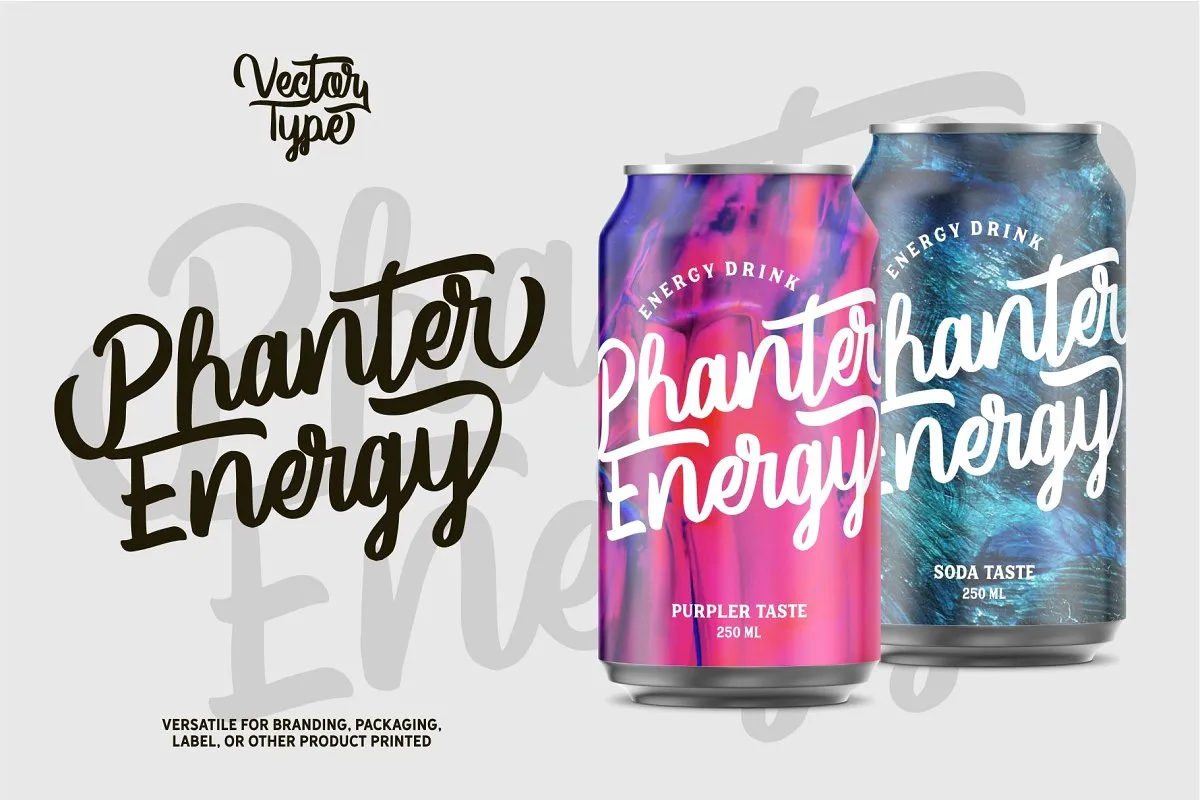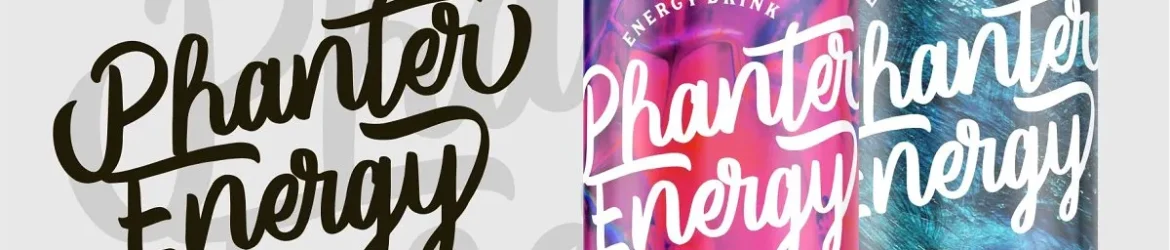
A Vector Type Script Font é uma fonte script que se destaca pelo seu estilo retrô fluido combinado com a elegância do letreiro à mão. Inspirada nos traços dinâmicos e nas linhas de curva sutis, essa fonte oferece um toque de sofisticação para qualquer projeto gráfico. Ideal tanto para criações digitais como físicas, a Vector Type Script Font é perfeitamente adaptável às demandas de design em diversas áreas, desde estampas de camisas até marcas e identidades visuais. Sujeito à sua criatividade, ela também torna-se um recurso valioso para projetos na web, como posts nas redes sociais ou criações de e-mail marketing. Afinal, quem não adoraria receber uma mensagem pessoal em uma camisa personalizada? Ou alegria em ver o seu nome escrito com cuidado nos anúncios do shopping da cidade? Esta fonte é o selo perfeito para um design que valoriza cada detalhe, seja na forma de branding ou no momento da celebração em um casamento.